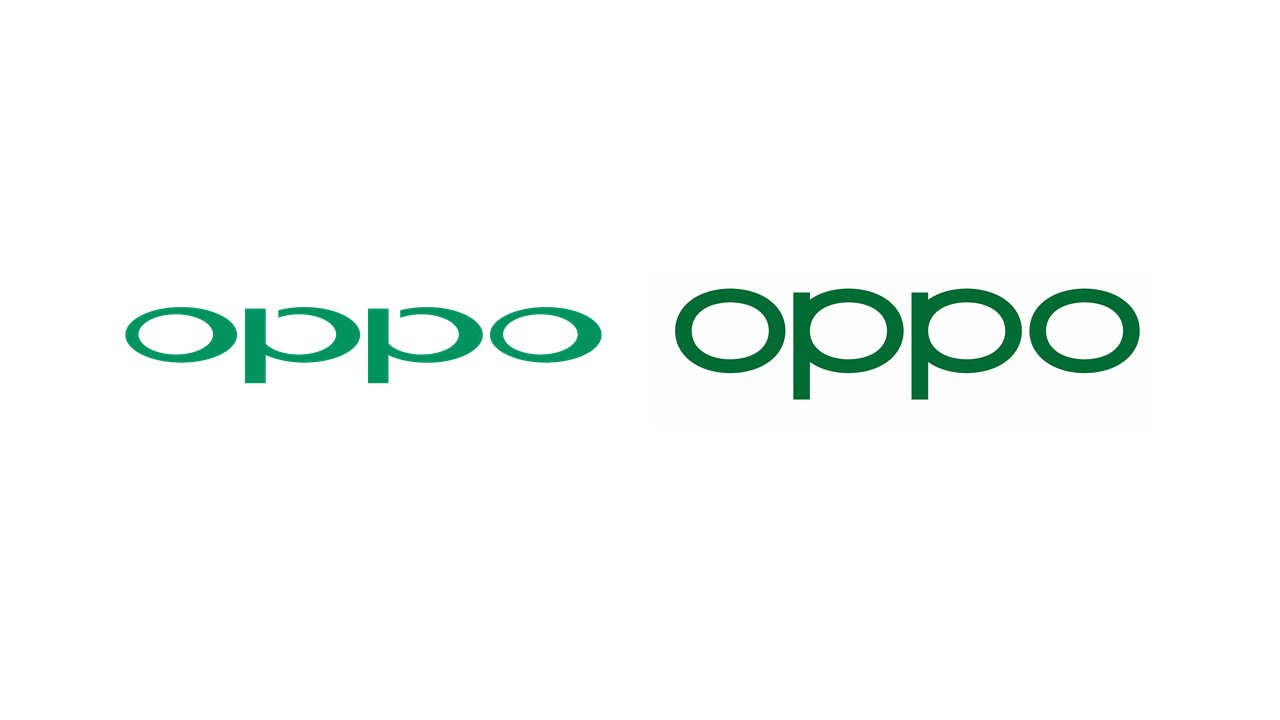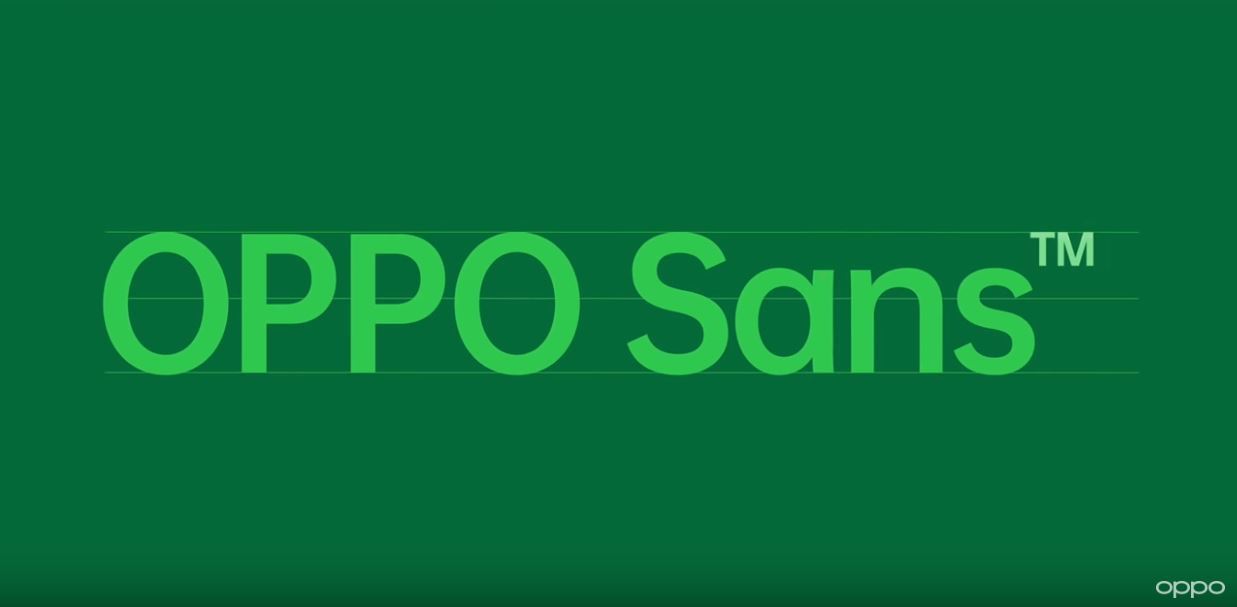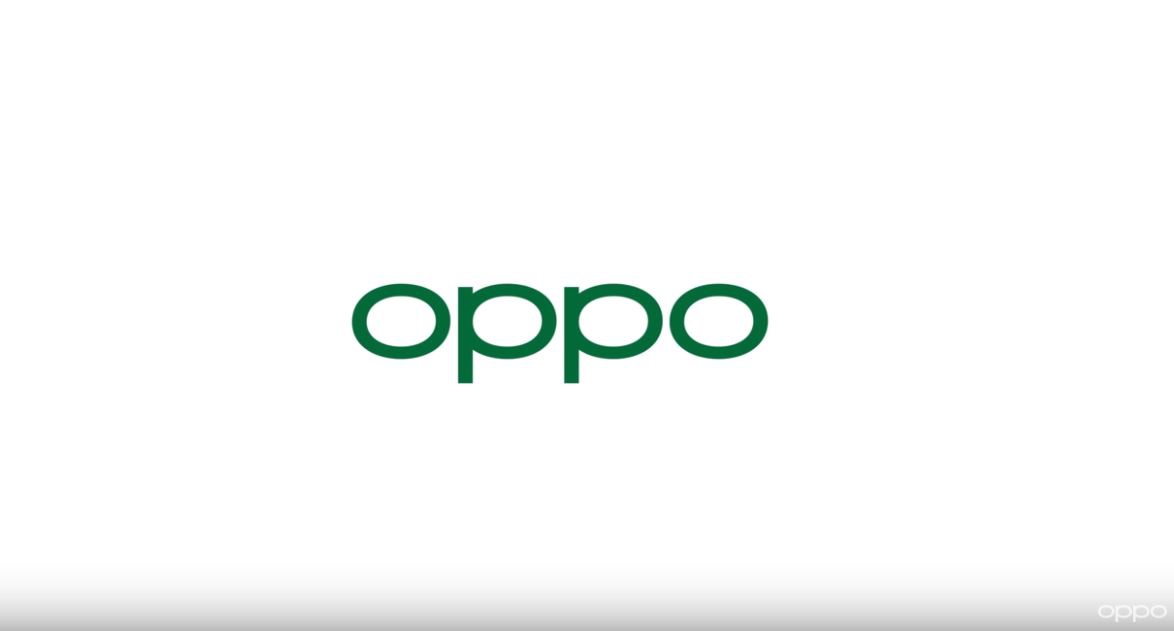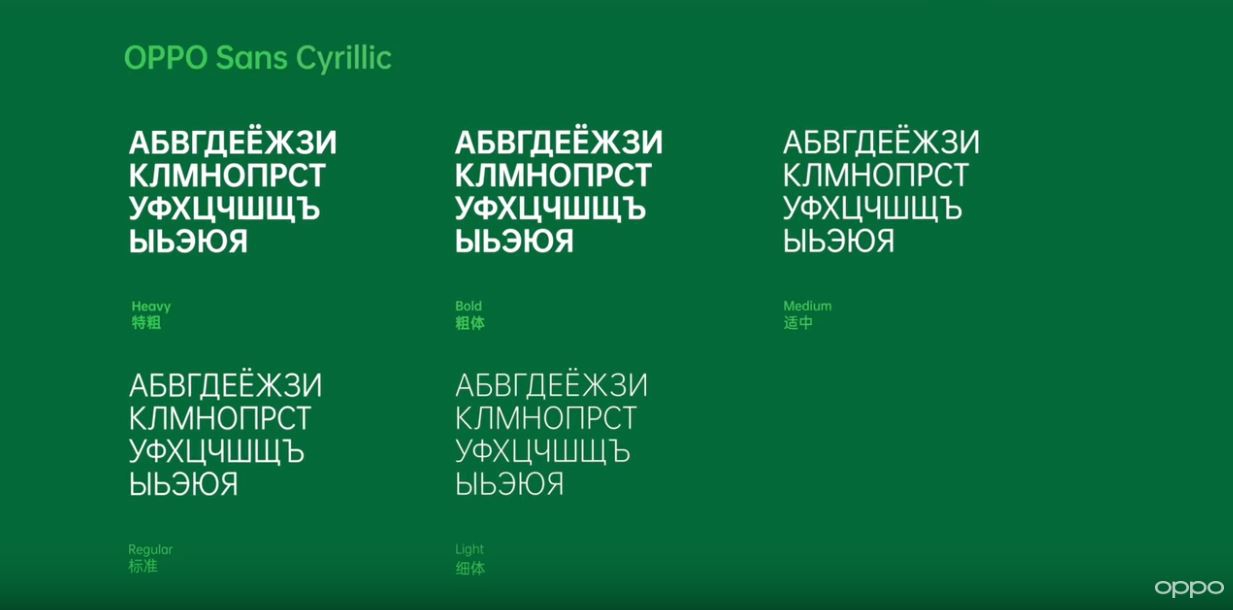
Новый фирменный стиль OPPO, представленный на глобальном рынке в апреле, теперь адаптирован и в России. Он, по словам создателей, отражает в себе постоянное развитие компании, ее уверенный рост и успех. Обновления затронули лого, корпоративные цвета, визуальную айдентику, также впервые был представлен фирменный шрифт.
Лого был разработан дизайнером и партнером легендарного нью-йоркского дизайн-бюро Pentagram Эдди Опара. OPPO и Pentagram совместно работали над новой визуальной концепцией около двух лет. За это время были проведены исследования рынков, на основе которых разработали и протестировали около тысячи макетов.
Новый логотип OPPO сочетает в себе классический стиль предыдущего дизайна и готический стиль нового кастомизированного шрифта OPPO Sans. Обновленный лого демонстрирует наследие бренда через использование объемных буквенных форм, которые легко оптимизируются для массового производства продукции компании.
Новый шрифт OPPO Sans является важной частью визуальной айдентики. Он еще раз демонстрирует то, что OPPO ценит качество, мастерство и уникальность в каждой детали. Фирменный шрифт поддерживается латиницей, кириллицей и китайскими иероглифами.
Логотип представлен вместе с новой цветовой гаммой, которая совершенствует фирменный зеленый цвет OPPO, усиливает его насыщенность в цифровом виде и представляет новую палитру для разных продуктовых линеек. Цветовая палитра предлагает множество вариантов, сохраняя при этом четкую идентичность бренда OPPO.
Чтобы отпраздновать новую айдентику, OPPO в партнерстве с датским художником Ларнетом Энгельбертсом выпустила видеоролик «OPPOlence». 70-секундное видео рассказывает историю создания нового логотипа с помощью арт-инсталляции, составленной из гигантских букв бренда.
Ролик разделен на четыре тематические части. Первая часть показывает пространство с музыкантами, которые олицетворяют изменение формы логотипа. Во второй части появляется танцующая девушка, раскрывающая элегантность нового шрифта. В третьей части ролика можно увидеть «зеленое» пространство с растениями, колышущимися от дождя. Оно отражает насыщенность нового фирменного цвета OPPO. В последней, четвертой части логотип представлен как одно целое.